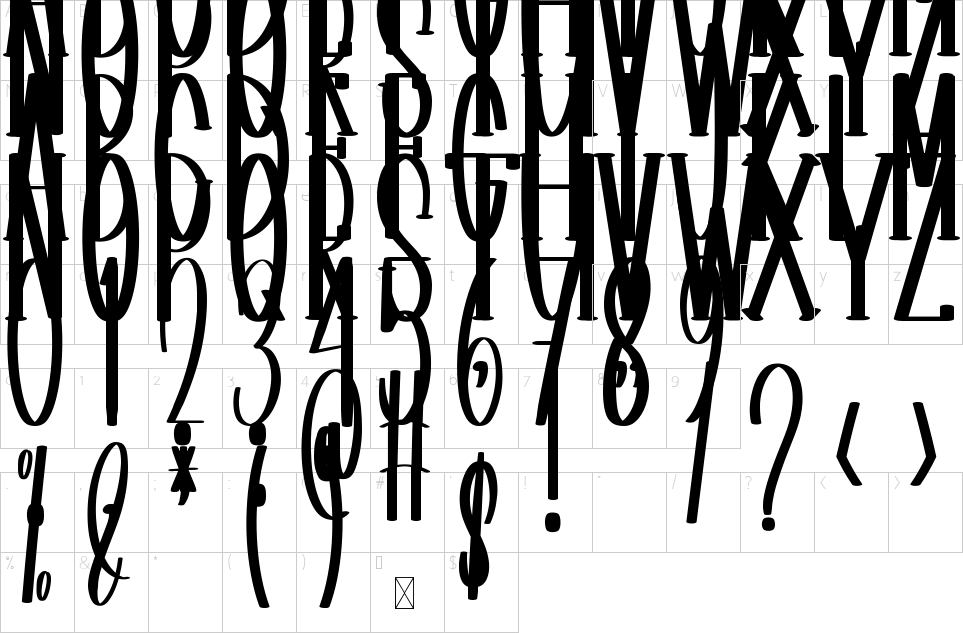
Antumn Blackboard Font – Download Grátis
A Antumn Blackboard Font é uma grata adição para aqueles que precisam de uma fonte de escrita rápida e clara. Desenvolvida pelo InermediaSTUDIO, esta fonte é perfeita para o ambiente escolar, escritos acadêmicos e até mesmo para uso em anúncios educacionais. Com uma estrutura levemente retangular e linhas sóbrias, a Antumn Blackboard oferece uma legibilidade ótima, especialmente em ambientes com texturas ou cores saturadas. Se você está procurando por uma fonte de qualidade que seja fácil de ler e de fácil acesso, a Antumn Blackboard Font é uma escolha inteligente. Sua simplicidade e legibilidade tornam-a uma fonte perfeita para uso em qualquer ambiente que exija uma escrita limpa e clara. Não perca a chance de melhorar seu projeto com a Antumn Blackboard Font.